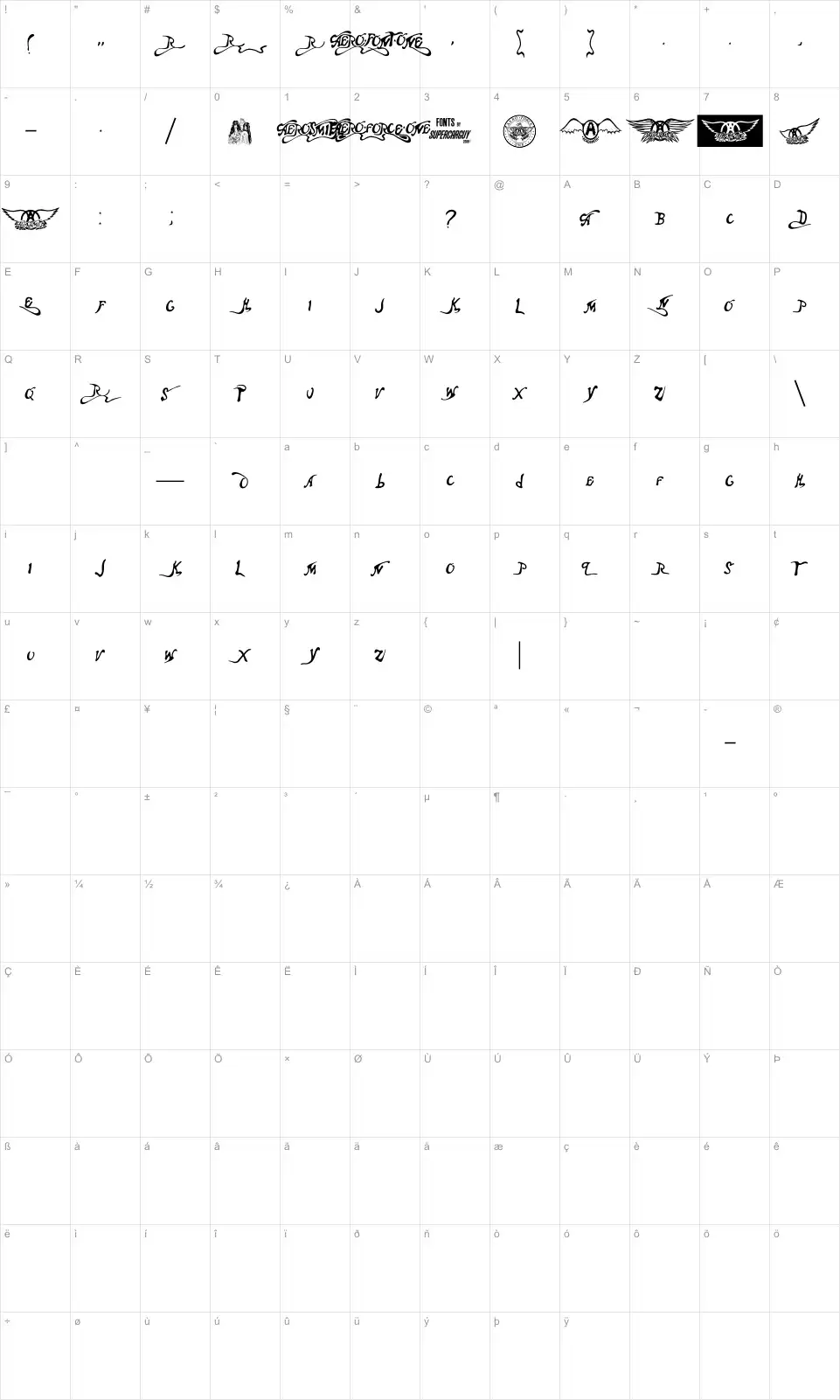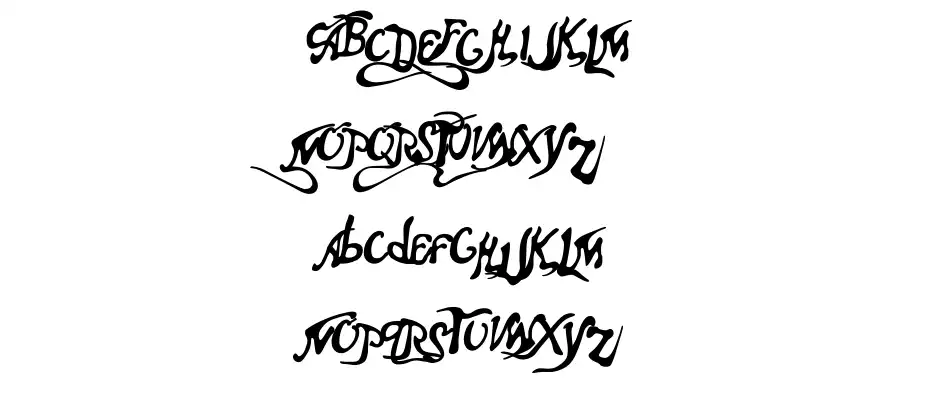
Aero Font One – Fonte Grátis
Aero Font One
A Aero Font One é uma fonte fantasia criada por Steve Ferrera, ideal para estilos modernos e criativos. Se você está à procura desta fonte especializada em categorias de fantasia, oferecemos a oportunidade de você descobrir como ela aparecerá em sua projeto antes de começar a usá-la. Seja para uso pessoal ou para adicionar um toque de originalidade a seu próximo projeto, esta fonte é uma ótima escolha. Licenciada de maneira gratuita para uso pessoal e disponível em formato TTF, a Aero Font One foi adicionada em 12 de julho de 2022, com downloads totais de 3609. Com um tamanho de 179 KB, é uma fonte de alta qualidade para quem procura um visual atraente e moderno.